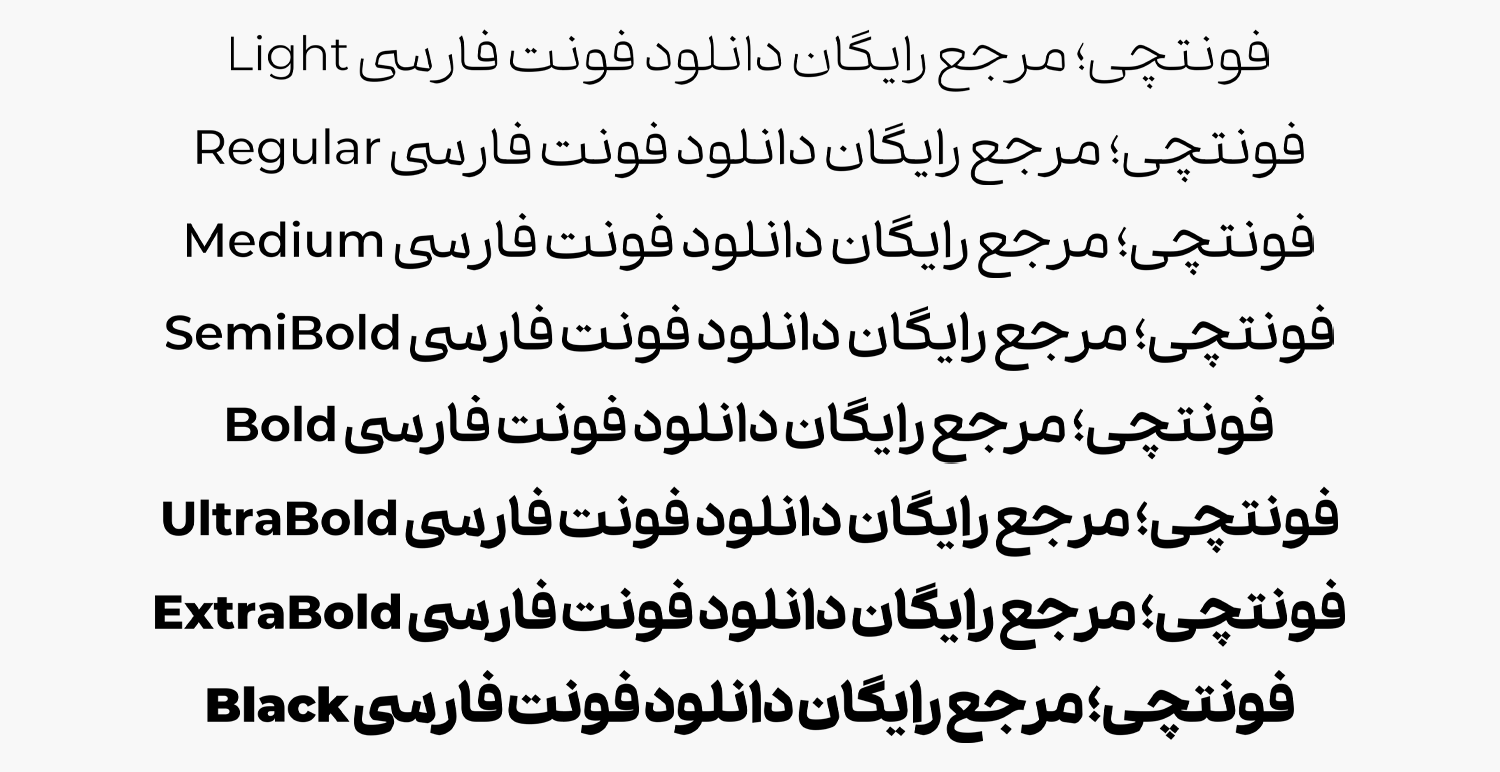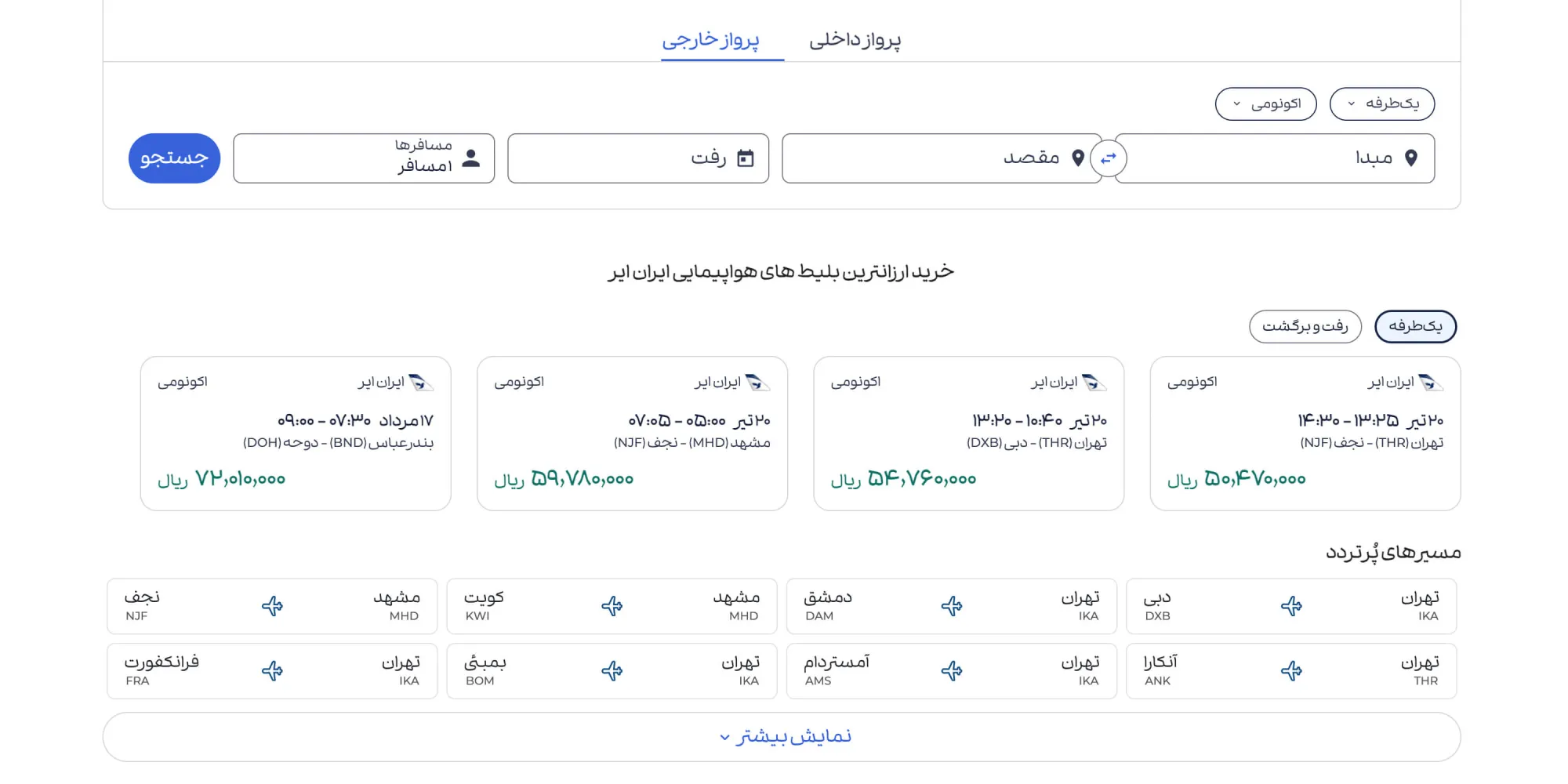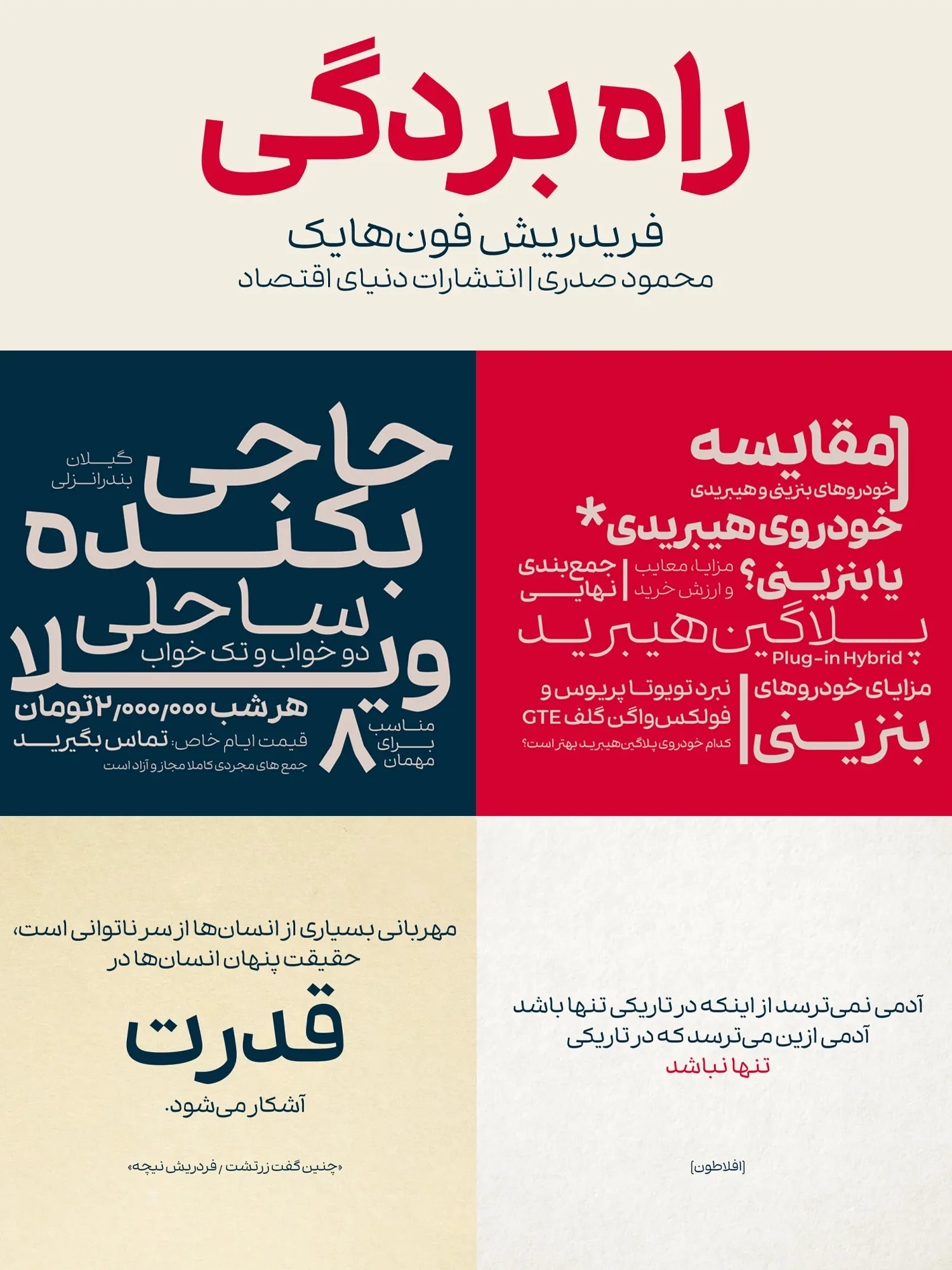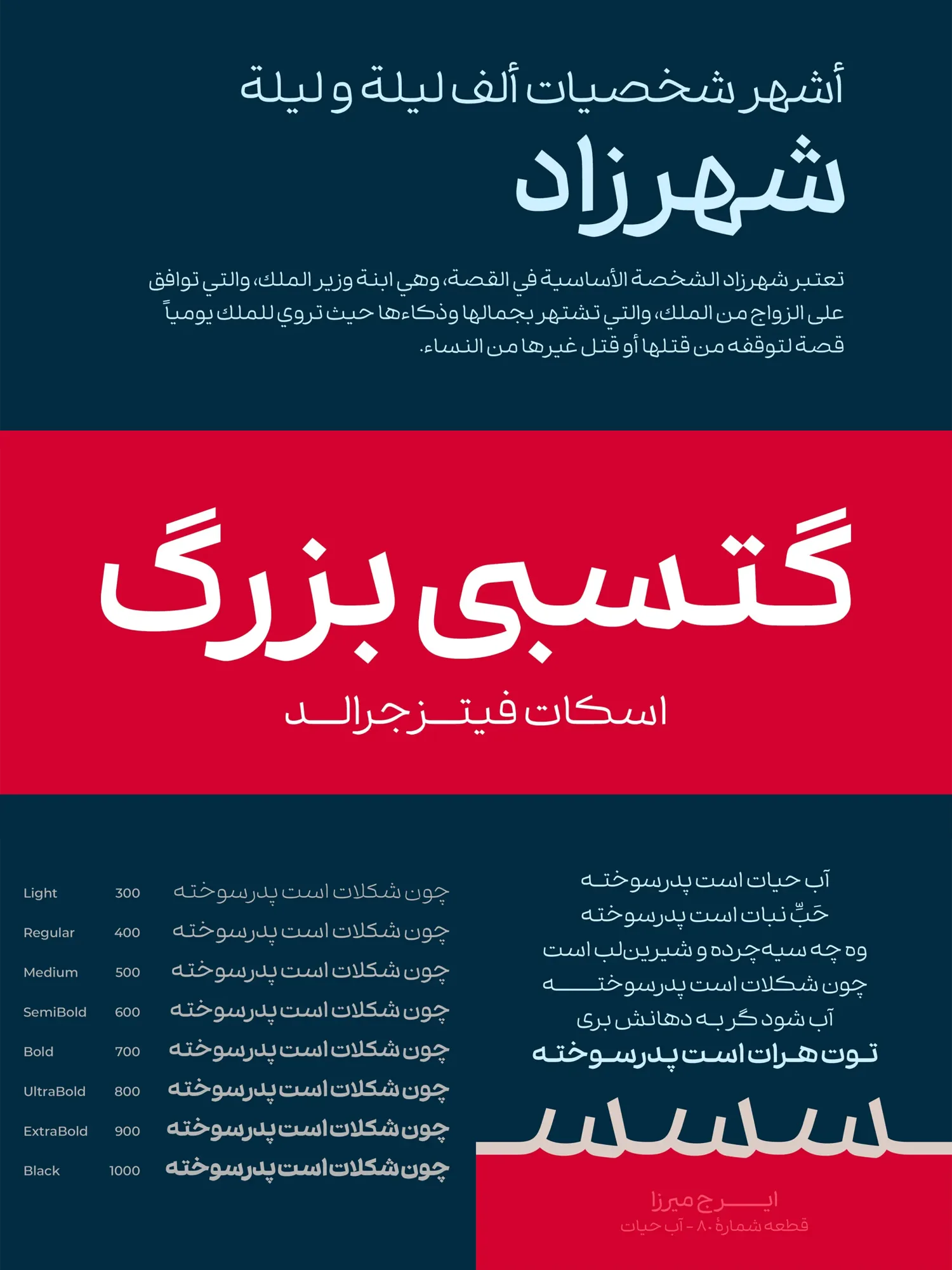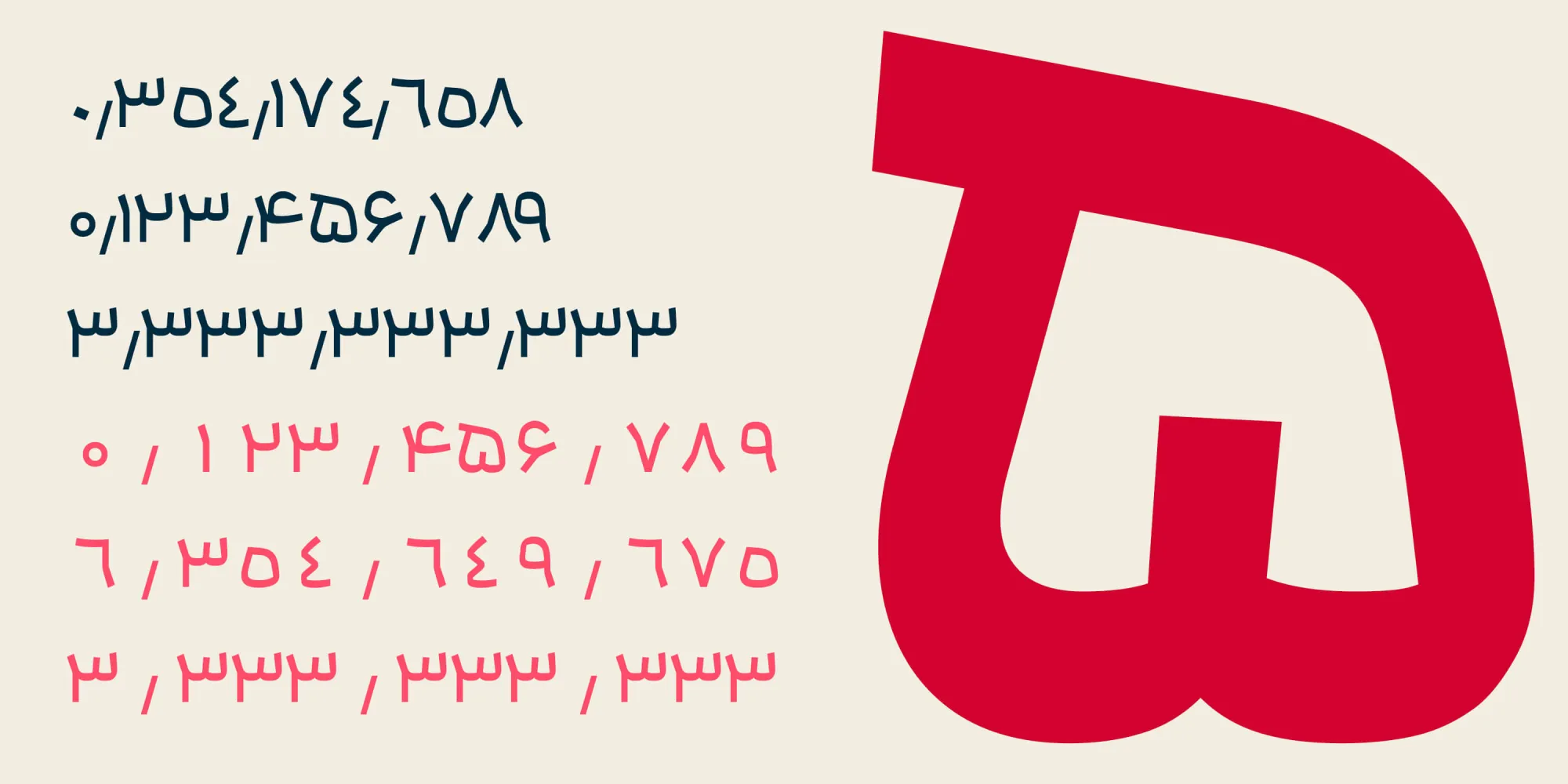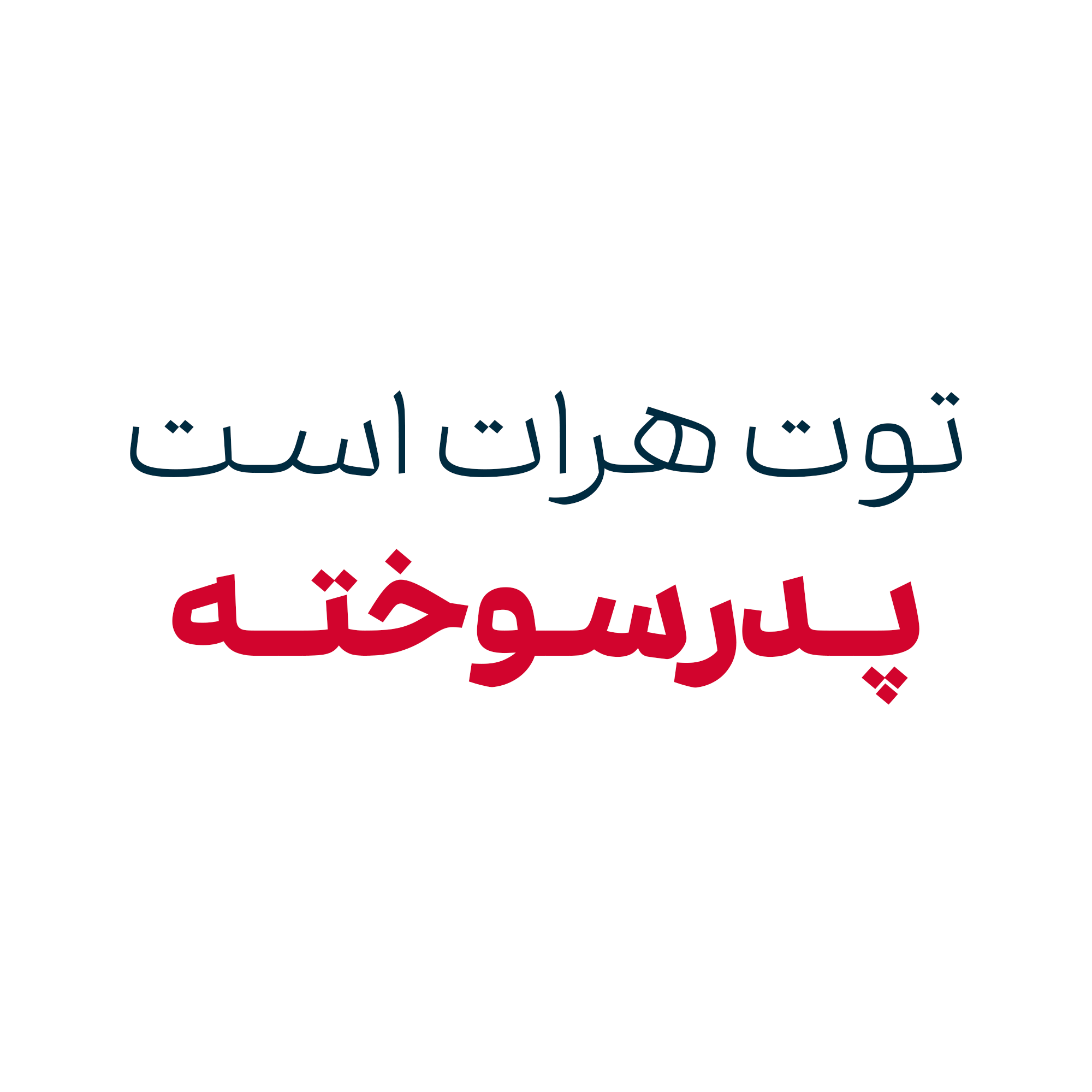
فونت شازده (Shazde)
فونت شازده (به انگلیسی: Shazde) از جدیدترین تایپفیسهای فارسی و عربی است که با تمرکز بر رابط کاربری، تایپوگرافی دیجیتال و خوانایی طراحی شده است. از این فونت میتوانید برای استفاده در رابط کاربری سایتها و اپلیکیشنهای موبایل بهترین استفاده را ببرید. فونت شازده رایگان نیست و با تنوع وزنی که دارد در ۳ بسته قابل خریداری است.
رضا بهلول این فونت را با تمرکز بر روی خوانایی در محیط دیجیتال طراحی کرده است که از زبان فارسی و عربی پشتیبانی کاملا استانداردی داشته و برای زبان انگلیسی ساختاری با همین ویژگیها را پشتیبانی میکند. در ادامه به نقد و بررسی این فونت جدید فارسی میپردازیم.
فونت شازده یک تایپفیس Sans-Serif مدرن است که با الهام از خط نسخ و اصول سنتی تایپوگرافی فارسی و عربی طراحی شده است. این فونت با هدف ارائه تجربهای روان و حرفهای در محیطهای دیجیتال مانند وبسایتها، اپلیکیشنهای موبایل و متنهای طولانی خلق شده است.
ویژگی کلیدی فونت شازده، خوانایی بالا (حتی در اندازههای کوچک) و نمایشگرهای با تراکم بالا (High-DPI) است که آن را به گزینهای ایدهآل برای طراحی رابط کاربری (UI) و تجربه کاربری (UX) تبدیل میکند.
شازده با ۸ وزن مختلف (از Thin تا Black) و پشتیبانی از ۲ سبک نقطه (گرد و مربع/مستطیل) ارائه میشود و شامل وریبل فونت (Variable Font) است که علاوه بر بهینه بودن برای سایتها، امکان تنظیم دقیق وزن و استایل را به طراحان میدهد. این تنوع، انعطافپذیری بالایی برای استفاده در پروژههای مختلف، از طراحی وب گرفته تا چاپ و تبلیغات، فراهم میکند.
خوانایی و وضوح بالا در هر اندازهای
به منظور داشتن عملکرد عالی در اندازههای کوچک، طراح فونت با کوتاه کردن ارتفاع حروفی مانند «الف» و «ل»، فضای عمودی متن را فشردهتر کرده و تراکم خطوط را کاهش داده است. این ویژگی باعث میشود متن در نمایشگرهای کوچک یا رزولوشنهای بالا، بدون افت کیفیت، خوانا و روان باقی بماند. این مزیت برای اپلیکیشنهای موبایل و وبسایتهای واکنشگرا بسیار حیاتی است.
با اینکه فونت برای استفاده در فضای دیجیتال طراحی شده، اما برای مطبوعات و چاپ نیز نسخهای عالی محسوب میشود. خصوصا در ابعاد بزرگتر برای چاپ بنر و بیلبورد که فونت زیبایی خارقالعادهای از خود به نمایش خواهد گذاشت.
طراحی مونولاین با حفظ اصول هندسی
فونت شازده با ساختاری نزدیک به مونولاین طراحی شده که ترکیبی از نرمی خطوط و تعادل هندسی را ارائه میدهد. این سبک طراحی، ظاهری مدرن و مینیمال به فونت بخشیده و آن را برای استفاده در رابطهای کاربری پیچیده و مقالات دیجیتال مناسب کرده است.
هر گلیف بهدقت طراحی شده تا در سیستمهای مبتنی بر گرید، چیدمانی منظم و یکدست ایجاد کند. این ویژگی بهخصوص برای طراحانی که به دنبال انسجام بصری در پروژههای خود هستند، بسیار ارزشمند است.
تنوع زبانی مناسب
شازده از زبانهای فارسی و عربی بهطور کامل پشتیبانی میکند و شامل اعداد فارسی است که برای طراحیهای بومی و کاربرپسند ضروری است.
این فونت برای پروژههای چندزبانه که نیاز به هماهنگی بین متون فارسی، عربی و حتی لاتین دارند، گزینهای مناسب است. هماهنگی بصری بین کاراکترهای فارسی و عربی، شازده را به انتخابی ایدهآل برای طراحیهای دوزبانه تبدیل کرده است.
علاوه بر اینها فونت در بخش اعداد برای هر زبان بهینه شده است. برای مثال ساختار نوشتار اعداد عربی «۴۵۶» به شکل استاندارد بوده و متمایز از اعداد فارسی «۴۵۶» تایپ میشوند.
بلکه میتوانید صرفا با آپلود یک فایل نسخه وریبل فونت، امکان استفاده از تمامی این وزنها را داشته باشید. نسخه وریبل امکان استفاده از سبک نقطهگذاری گرد یا مربعی را نیز فراهم میکند.
فونت شازده در بعد مقایسه
برای تحلیل بهتر، فونت شازده را با چند فونت محبوب دیگر مقایسه میکنیم:
| فونت | خوانایی | وزن | سبک | کاربرد |
|---|---|---|---|---|
| شازده | بالا | ۸ | مدرن، مونولاین | وب، UI |
| ایران سنس | بالا | ۹ | مدرن، مینیمال | وب، UI، برندینگ |
| وزیر | بالا | ۱۱ | کلاسیک، رسمی | وب، مقالات، چاپ |
| دانا | بالا | ۱۳ | مدرن، هندسی | وب، UI، گرافیک |
شازده در مقایسه با ایران سنس، به دلیل طراحی مونولاین و فشردگی عمودی، برای رابطهای کاربری متراکمتر مناسبتر است. در مقابل فونت وزیر، شازده ظاهری مدرنتر دارد، اما به دلیل پولی بودن، ممکن است برای پروژههایبا بودجه پایین، کمتر ترجیح داده شود.
فونت دانا نیز با تنوع وزن بالاتر، انعطاف بیشتری برای پروژههای گرافیکی دارد، اما شازده در خوانایی بهتری در اندازههای کوچک دارد.